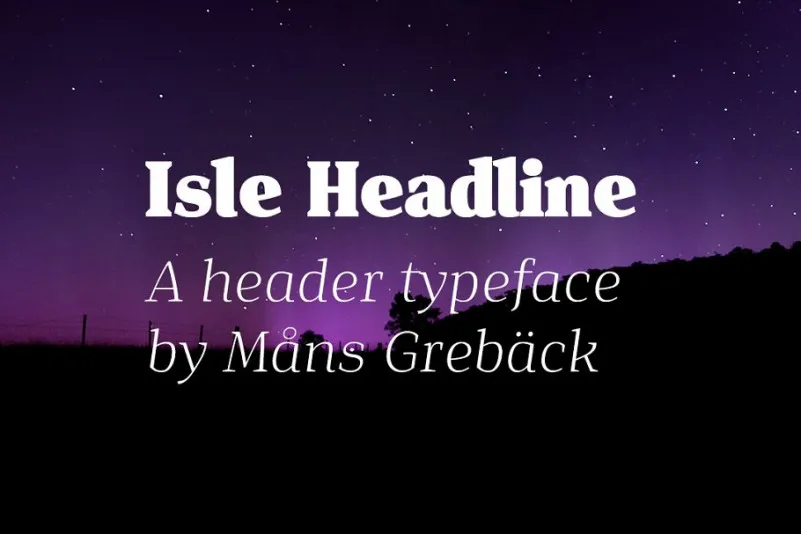
Embora a Isle Headline seja uma fonte serif cuidadosamente criada por Mans Greback durante 2018 e 2019, ela é mais do que apenas um recurso visual para cabeçalhos e títulos de grande importância. Com quatro pesos distintos, cada um acompanhado da sua itálica correspondente, a Isle Headline oferece uma variedade impressionante que inclui styles como Light, Medium, Bold e Black. Este é o tipo de fonte ideal para destacar elementos importantes em sua página ou design gráfico, seja em cabeçalhos ou como uma combinação com o estilo da sua escolha. Com seu formato serif e sua aparência aguda e atenta, a Isle Headline se destaca não apenas por oferecer um look impecável, mas também por ser adaptada para ser usada em grande proporção. Esta fonte é perfeita tanto para cabeçalhos quanto para texto de corpo, onde você desejará que o seu design seja suave e agradável ao olhar. A Isle Headline também se combina bem com sua irmã, a Isle Body, outra fonte serif que mantém as mesmas estruturas básicas, mas apresenta um tom mais suave ideal para textos de corpo e tamanhos menores. Com uma variedade vasta de opções, seja você um designer gráfico ou editor de conteúdo digital, temos certeza de que a Isle Headline será a escolha perfeita para criar designs impecáveis e visuais atrativos.